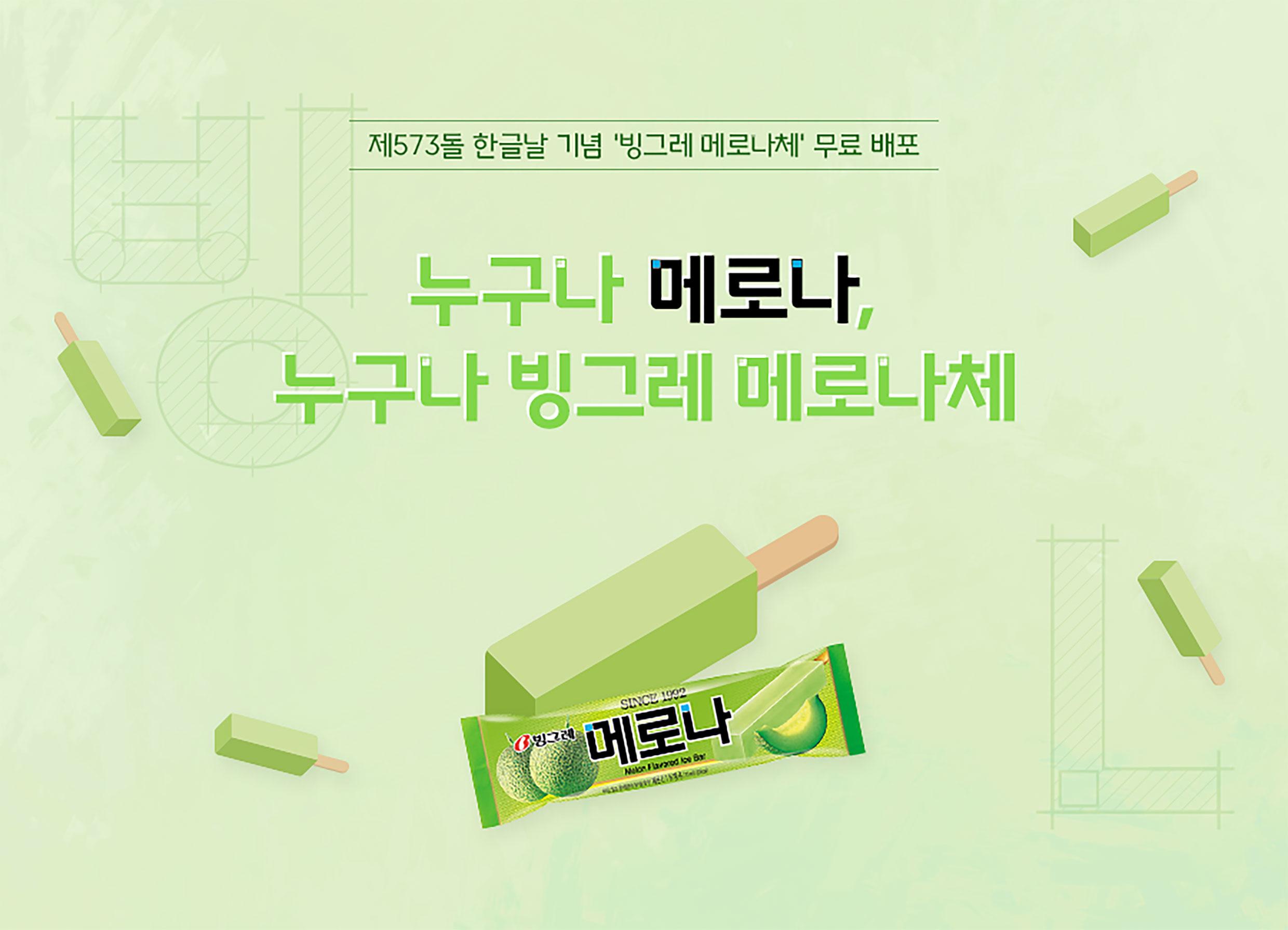
㈜윤디자인그룹, 옛한글 지원 ‘빙그레 메로나체’ 글꼴 개발
㈜윤디자인그룹이 한글날을 맞아 ‘빙그레 메로나체’를 개발한다.
㈜윤디자인그룹이 옛한글까지 지원하는 ‘빙그레 메로나체’ 글꼴을 개발해 관심을 모으고 있다.
‘메로나’는 국내 기업 빙그레에서 1990년대 초반 출시된 메론 맛 아이스크림으로 윤디자인그룹을 통해 약 30년 만에 전용서체인 ‘메로나체’를 갖게 됐다. 순한글의 기업명인 빙그레에서 보듯 평소 한글 글꼴이 부족하다는 점에 관심을 가져왔다. 이같은 인식을 바탕으로 국내 대표적인 폰트 기업 ㈜윤디자인그룹과 함께 2016년 '빙그레체(바나나맛우유), 2017년 빙그레체Ⅱ(투게더), 2018년 빙그레 따옴체, 그리고 2019년 네 번째 글꼴, 빙그레 메로나체를 개발했다고 전했다.
빙그레 메로나체는 로고에 담긴 메로나만의 아이덴티티를 뉴트로 감성으로 재해석한 글꼴이며 각진 네모가 아닌 부드럽게 네모난 메로나를 형상화 했다. 반듯하고 세련된 디자인으로 곡선을 최소화하고 ‘메’와 ‘나’에 메로나 로고만의 특징적 요소를 반영했으며 영문에서는 이를 ‘L’에 적용했다고 한다. 글자마다 적정 폭을 적용해 문장 작성시 글의 흐름이 일정하도록 설계했으며 적정 자간과 적정 띄어쓰기를 설정했다. 시각 중심선이 상단에 배치돼 정돈된 느낌과 뛰어난 판독성을 갖는 것 또한 특징이다.
빙그레 메로나체는 총 2종(Bold, Regular)으로 한글 11,172자와 영문 94자, KS 심볼 986자로 구성됐다. 특히 옛한글까지 지원해 한글 글꼴로서의 특별한 존재감을 더하고 있다. 국문학자와 디자이너의 자문을 반영한 결과물로 훈민정음 서문의 옛한글 31자가 추가됐다. 옛한글 지원으로 더욱 유의미해진 빙그레 메로나체는 현재 제573돌 한글날을 맞아 누구나 내려받아 사용할 수 있도록 무료폰트를 배포중이다.